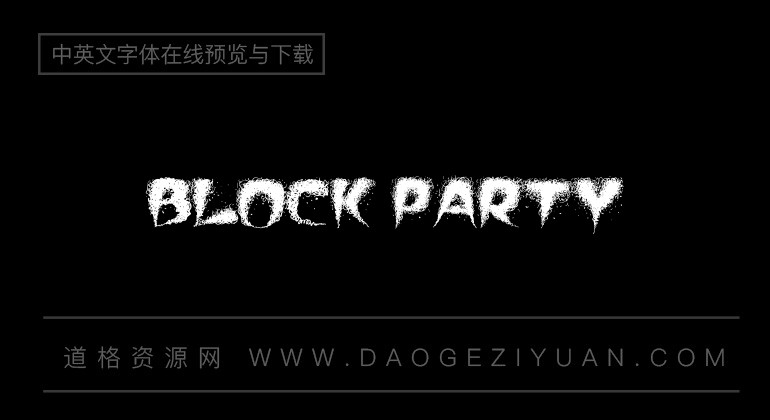
Block Party是一种现代、粗糙的字体,它的特点是字母的边缘非常粗糙,仿佛是用方块拼成的。这种字体常常被用于各种设计中,如海报、标志、广告、游戏等。它的设计灵感来自于涂鸦和字母拼贴艺术,旨在传达一种年轻、时尚、自由的感觉。这种字体的特点是字母间的空隙较小,字母本身也较为紧凑,因此在使用时需要注意排版和字距的调整。总之,Block Party是一种非常有个性的字体,适合用于需要突出个性和创意的设计中。内容介绍
Block Party是一款非常不错的手写艺术字体,具有很好的视觉感,适合于文化类的宣传设计、商业类品牌的广告和产品包装设计以及个性化文字排版等较多场景。